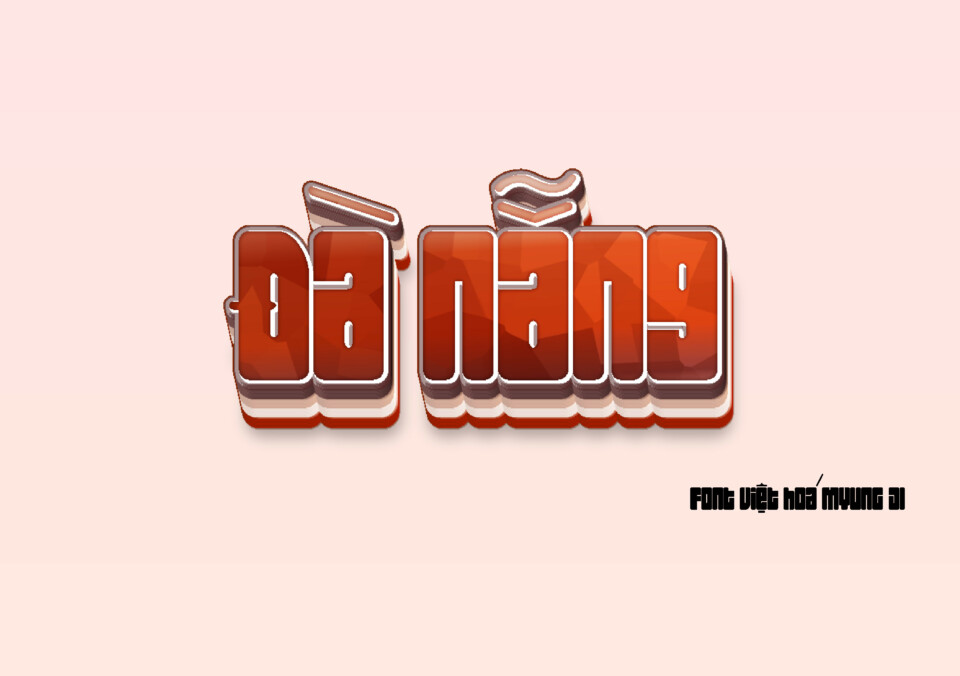
Font việt hóa MJ Paztime
• Dưới đây là một số điểm nổi bật về font này:
1. Thiết kế hiện đại và tinh tế: MJ Paztime sở hữu kiểu dáng thanh thoát, với các đường nét mềm mại nhưng vẫn giữ được sự chắc chắn. Điều này không chỉ tạo ra sự hấp dẫn về mặt thị giác mà còn giúp tăng cường trải nghiệm người dùng. Font này rất phù hợp cho các sản phẩm in ấn, quảng cáo, và các thiết kế trực tuyến.
2. Hỗ trợ đầy đủ tiếng Việt: Một trong những ưu điểm nổi bật của MJ Paztime là khả năng hiển thị hoàn hảo các ký tự tiếng Việt, bao gồm cả các dấu thanh. Điều này giúp người dùng dễ dàng sử dụng font trong bất kỳ loại văn bản nào mà không gặp phải vấn đề về hiển thị ký tự.
3. Độ dễ đọc cao: MJ Paztime được thiết kế với tiêu chí dễ đọc, giúp người dùng có thể nhận diện các ký tự một cách nhanh chóng và chính xác. Điều này đặc biệt quan trọng trong các tài liệu dài hoặc khi sử dụng trong môi trường trực tuyến, nơi mà người đọc cần nhanh chóng nắm bắt thông tin.
4. Tính linh hoạt trong ứng dụng: Font này có thể được sử dụng trong nhiều lĩnh vực khác nhau, từ thiết kế logo, poster, đến các sản phẩm truyền thông trực tuyến như website và mạng xã hội. MJ Paztime là sự lựa chọn hoàn hảo cho các dự án cần sự sáng tạo và phong cách.
5. Cảm hứng sáng tạo: Với nét đẹp hiện đại và trẻ trung, MJ Paztime mang lại cảm hứng cho người dùng trong quá trình sáng tạo nội dung. Font này không chỉ là một công cụ hỗ trợ mà còn là một phần quan trọng trong việc thể hiện cá tính và phong cách riêng của mỗi dự án.
Tóm lại, MJ Paztime không chỉ đơn thuần là một kiểu chữ mà còn là một phần không thể thiếu trong bộ công cụ sáng tạo của những người làm nghệ thuật và thiết kế tại Việt Nam. Sự kết hợp giữa tính năng tối ưu và thiết kế đẹp mắt khiến MJ Paztime trở thành lựa chọn lý tưởng cho bất kỳ ai đang tìm kiếm một font chữ chất lượng cho tiếng Việt.